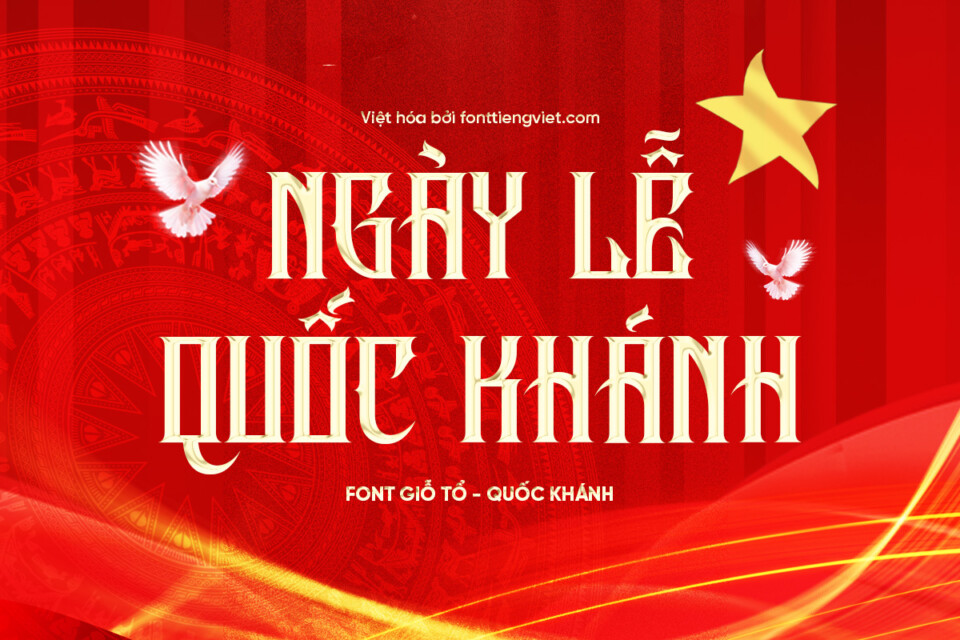
Font Việt hóa 1FTV VIP Rectinos – Font Giỗ tổ Quốc KhánhGiới thiệu Font Việt hóa 1FTV VIP Rectinos – Font Giỗ tổ Quốc KhánhTrong các hoạt động giáo dục và thiết kế phong trào tại nhà trường, việc lựa chọn một Font Miễn Phí phù hợp là vô cùng quan trọng. Bộ Font Việt hóa 1FTV VIP Rectinos – Font Giỗ tổ Quốc Khánh chính là giải pháp hoàn hảo, mang lại sự trang nghiêm nhưng không kém phần hiện đại cho các tác phẩm đồ họa học đường.Ưu điểm nổi bật của bộ font chữ đặc biệt nàyThiết kế tối ưu cho tiếng ViệtĐược chau chuốt kỹ lưỡng về hệ thống dấu thanh, font chữ này giúp thầy cô và học sinh dễ dàng soạn thảo văn bản, thiết kế bảng tin, làm slide thuyết trình hay làm báo tường mà không lo bị lỗi hiển thị. Từng nét chữ mang phong cách vuông vức, vững chãi, tạo cảm giác tin cậy và trang trọng.Phù hợp với các sự kiện lịch sử trọng đạiVới tên gọi đầy ý nghĩa, bộ font này cực kỳ thích hợp để ứng dụng vào các dịp lễ lớn của dân tộc như Ngày Giỗ tổ Hùng Vương hay Ngày Quốc Khánh mùng 2 tháng 9. Kiểu dáng vừa mang hơi thở truyền thống, vừa mang nét chấm phá của thiết kế đương đại giúp các banner, áp phích cổ động trở nên sinh động, dễ tiếp cận hơn với thế hệ trẻ.Ứng dụng Font Việt hóa 1FTV VIP Rectinos – Font Giỗ tổ Quốc Khánh trong học đườngHọc sinh có thể dùng font chữ này để làm tiêu đề bài tập lớn, thiết kế thiệp chúc mừng hoặc các ấn phẩm truyền thông cho câu lạc bộ. Giáo viên cũng dễ dàng sáng tạo bài giảng trực quan, thu hút sự chú ý của học sinh hơn.Tải ngay để sáng tạo bài học ý nghĩaViệc sở hữu công cụ thiết kế chuẩn SEO sẽ giúp nâng cao chất lượng thẩm mỹ cho mọi sản phẩm giáo dục. Hãy truy cập ngay hệ thống để tải xuống bộ Font Miễn Phí, Font Việt Hóa, Font Việt hóa 1FTV VIP Rectinos – Font Giỗ tổ Quốc Khánh hoàn toàn tiện lợi và trải nghiệm sự khác biệt trong từng nét chữ hôm nay.
Font Việt hóa 1FTV VIP Rectinos – Font Giỗ tổ Quốc Khánh